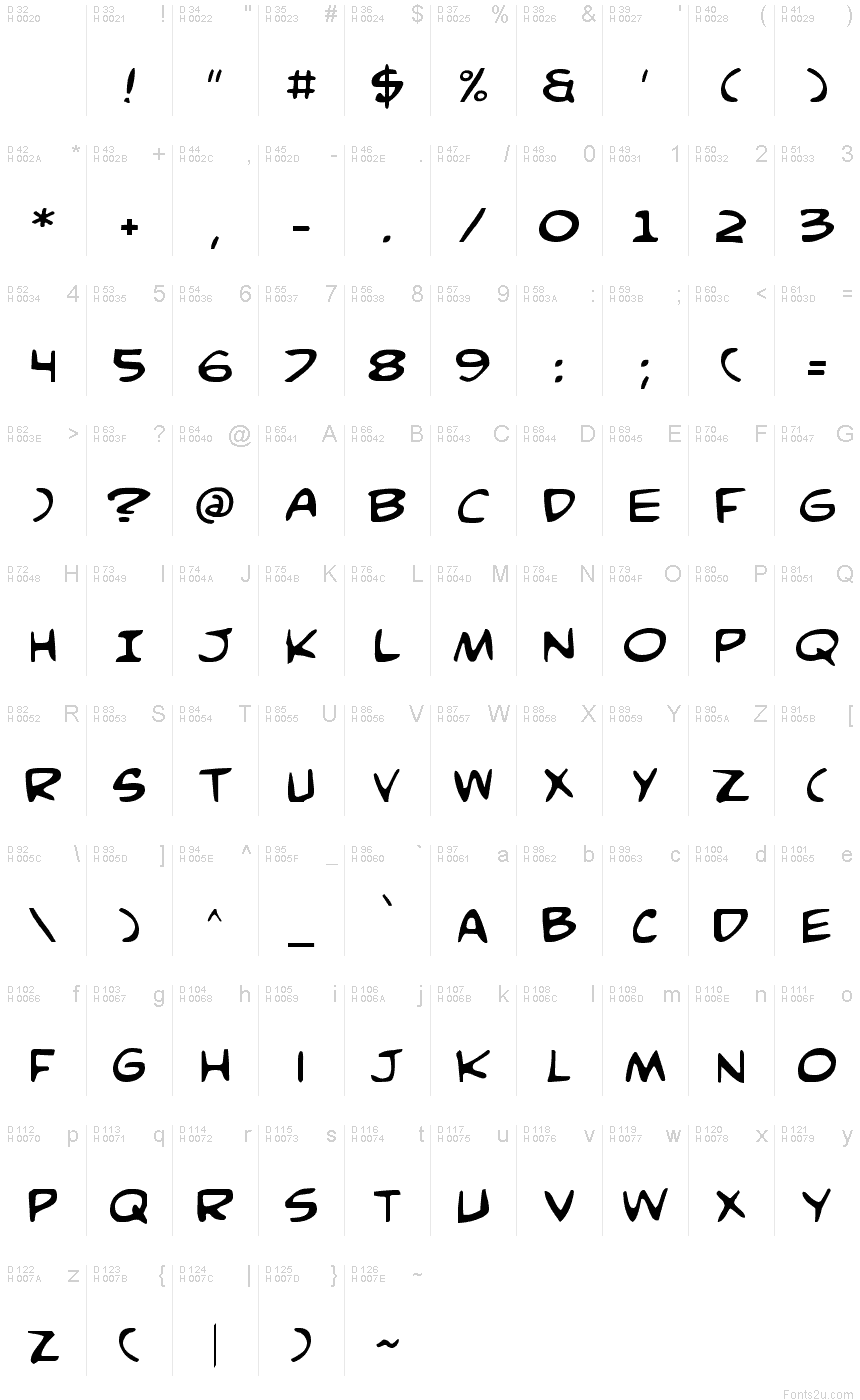
Comic Book Commando
Font Comic Book Commando od Iconian Fonts to bezpłatny komiksowy krój akcydensowy o odważnym, malarskim charakterze, który wygląda jak wyjęty prosto z ręcznie rysowanej planszy. Litery sprawiają wrażenie rysowanych tuszem i są przyjemnie nierówne – z grubymi pociągnięciami, zaokrąglonymi rogami i tym klasycznym klimatem sobotnich kreskówek. Silny, poziomy przepływ słów sprawia, że nagłówki czytają się jak pewna siebie dymkowa wypowiedź, a nie sztywny tytuł.
Używając Comic Book Commando, wprowadzisz tę wyrazistą energię do okładek komiksów, zinów, plakatów, tytułów książek dla dzieci, miniatur na YouTube, interfejsów gier i oznaczeń konwentowych. Hojne kształty świetnie wyglądają nawet przy dużych rozmiarach, więc nie bój się ich powiększać dla uzyskania maksymalnego efektu. W przypadku tekstów głównych lub podpisów zestaw ten darmowy font z czystym, neutralnym bezszeryfowym krojem, aby grafiki i nagłówki pozostały w centrum uwagi.